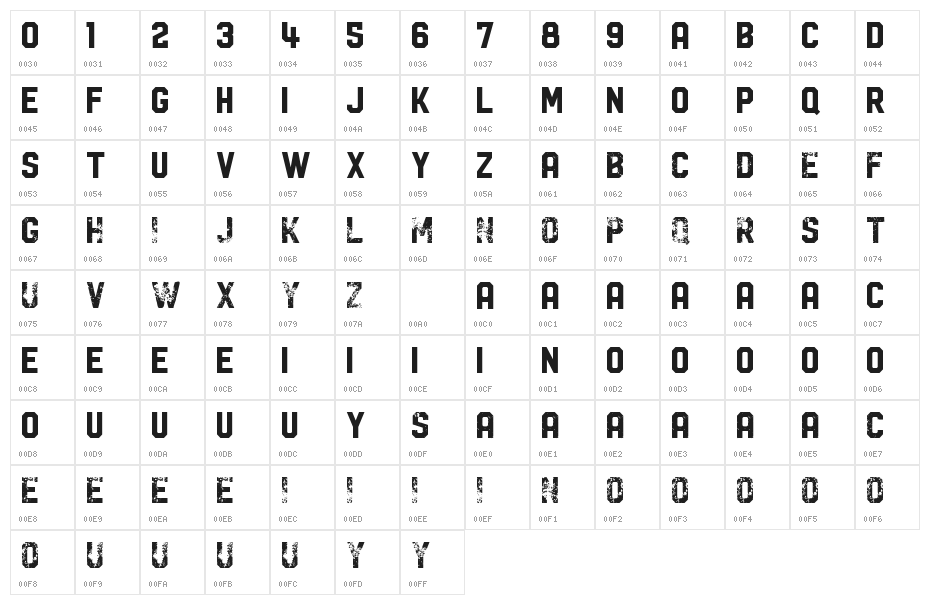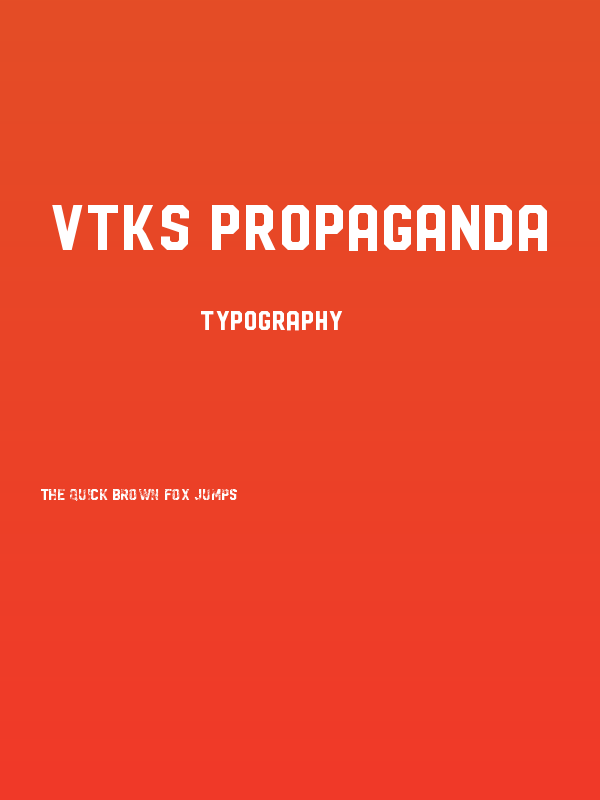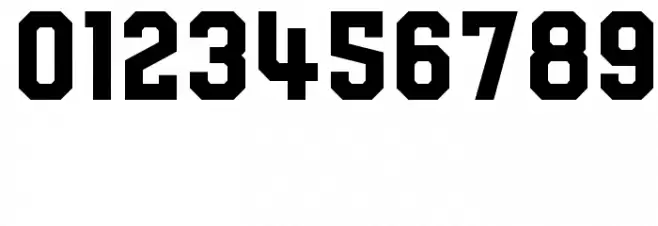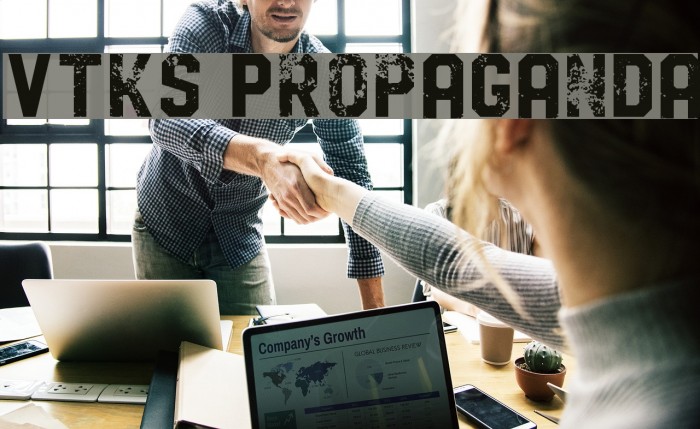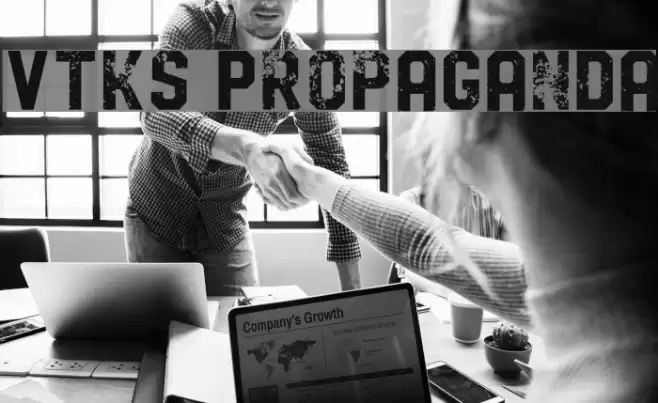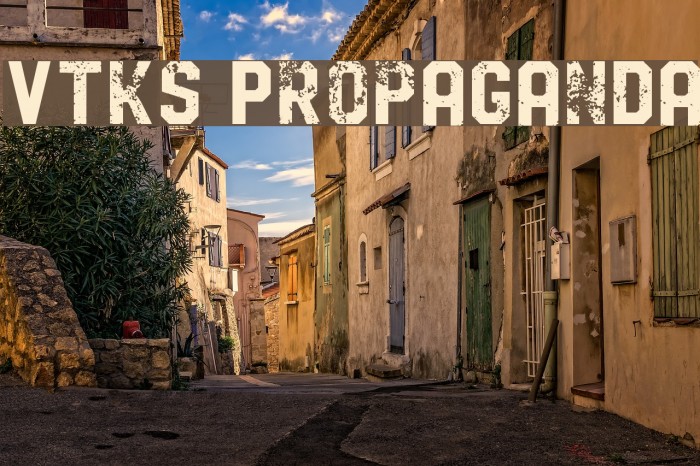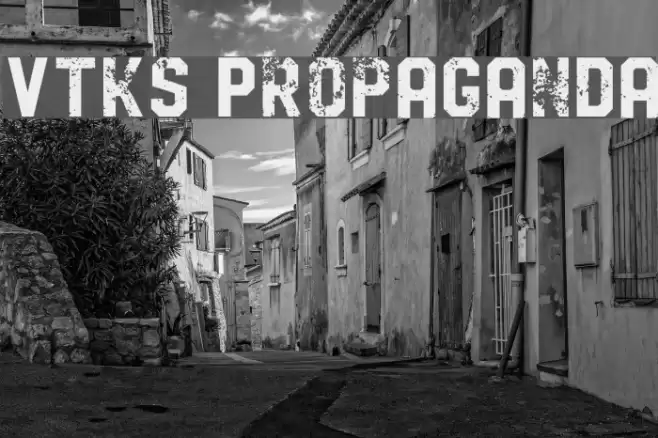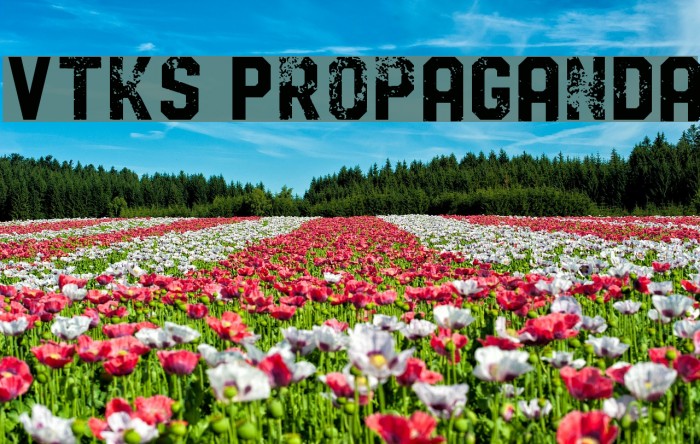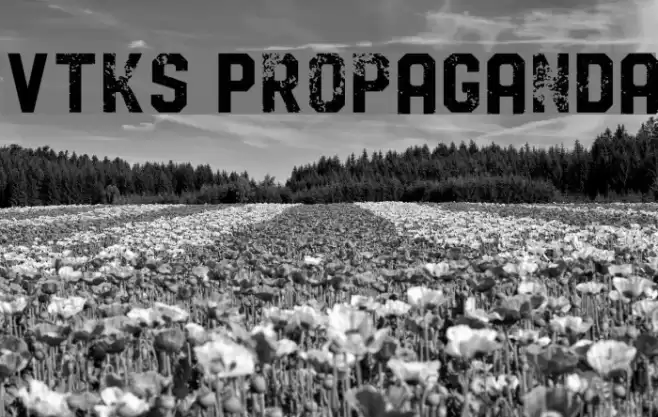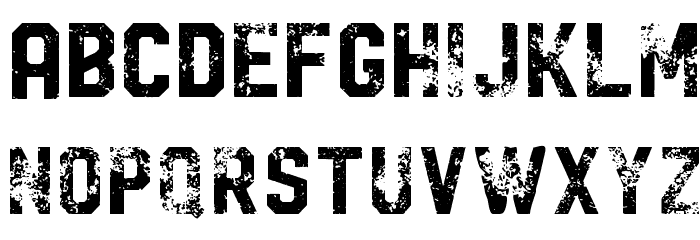
Vtks Propaganda Font
| Gesamtstil | Industrial, Vintage |
| Anwendungsfall | Headlines, Posters, Branding |
| Vorgeschlagene Projekte | Ideal for posters, branding, and headlines that need a strong, industrial feel. |